变体字设计是字体设计里重要的一部分,因为它的多变性极高,相较于普通字体,变体字的字体识别性更高,给人们的印象更为深刻。解决多平台系统问题的一个解决方案就是可变字体。蒙纳预测,这种字体在未来十年将大幅增加。除了趋势,当涉及到在印刷品、数码、AR、虚拟现实、(当然还有)现实世界中创建一致的品牌语言和语调时,可变字体为设计师提供了更大的范围和更大的自由。感兴趣的小伙伴我们一起来看看变体字的奇妙之处吧。
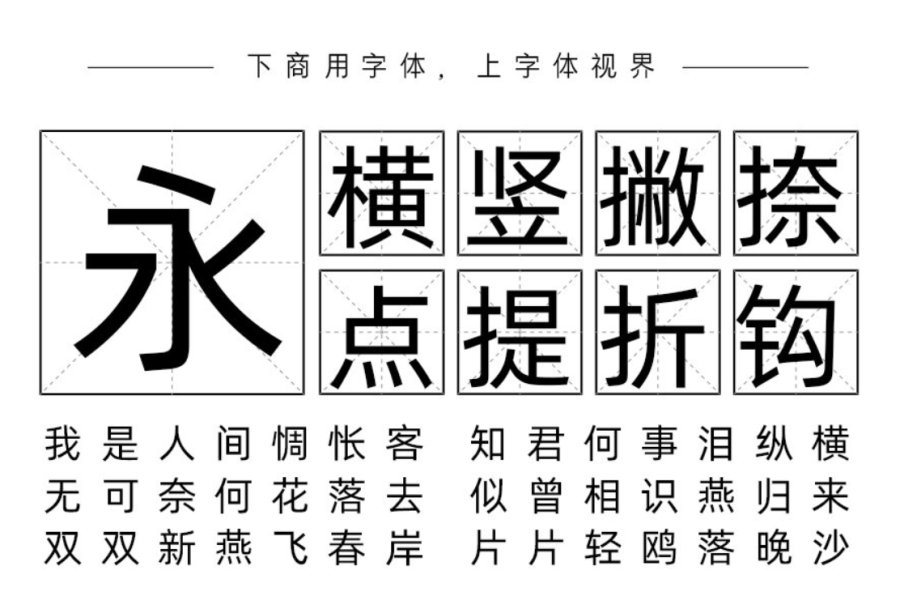
“阿里巴巴普惠体”是TCA字体大赛亚洲区唯一获奖作品。阿里巴巴普惠体共收录 116,895 个全形汉字(含 5 个字重),西文 Alibaba Sans 共 7,205 个拉丁字母(2 种风格、共 11 个字重),覆盖 172 个语种(覆盖大部分欧语国家)。字体极具现代感、字形方正大方,不仅包含突显企业品牌个性的标题字体,还囊括了更为实用的内文字体,适合于一个场景下的多种应用。
义启字库也有一款原创设计的变体字“iekie Benus”。Benus是一款动态的字体,波浪形的线条像一条条随波飘扬的海草,极具创意性。充满创造力与可能性,应用在logo设计、包装设计、标题、广告设计等领域可以反映一个品牌的形象。
蒙纳评价变体字说“在过去,设计师可能会被限制为一个网站使用四到五种字体,但可变字体给他们提供了一个更广阔的字体调配板,从而对一个品牌的身份有更大的控制力。” 一款极具变化性的字体可以展现出设计的多元魅力,感兴趣的你可以点击搜字体购买了解关于字体的更多信息。